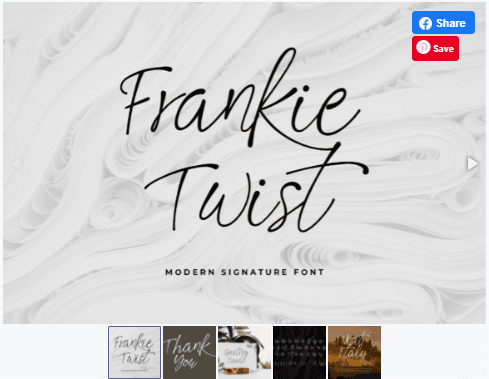
Frankie Twist Font
Frankie Twist - это тонкий буквенный и хорошо сбалансированный рукописный шрифт. Теплый, романтичный и веселый, этот шрифт превратит каждую вашу проектную идею в настоящие произведения искусства. Получайте удовольствие от этого красивого шрифта и исследуйте его бесконечные вариации.